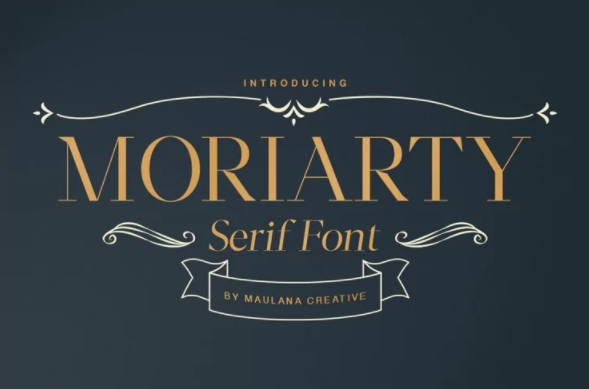
[Fontbundles] Moriarty Serif Font (2022)
Moriarty Serif - соврСмСнный повсСднСвный ΡˆΡ€ΠΈΡ„Ρ‚, идСально подходящий для Π·Π°Π³ΠΎΠ»ΠΎΠ²ΠΊΠΎΠ², Π»ΠΎΠ³ΠΎΡ‚ΠΈΠΏΠΎΠ², ΠΆΡƒΡ€Π½Π°Π»ΠΎΠ² ΠΈ любого Ρ€Π΅Π΄Π°ΠΊΡ†ΠΈΠΎΠ½Π½ΠΎΠ³ΠΎ Π΄ΠΈΠ·Π°ΠΉΠ½Π°, Π° Ρ‚Π°ΠΊΠΆΠ΅ для Ρ‡ΠΈΡ‚Π°Π±Π΅Π»ΡŒΠ½ΠΎΠ³ΠΎ основного тСкста.